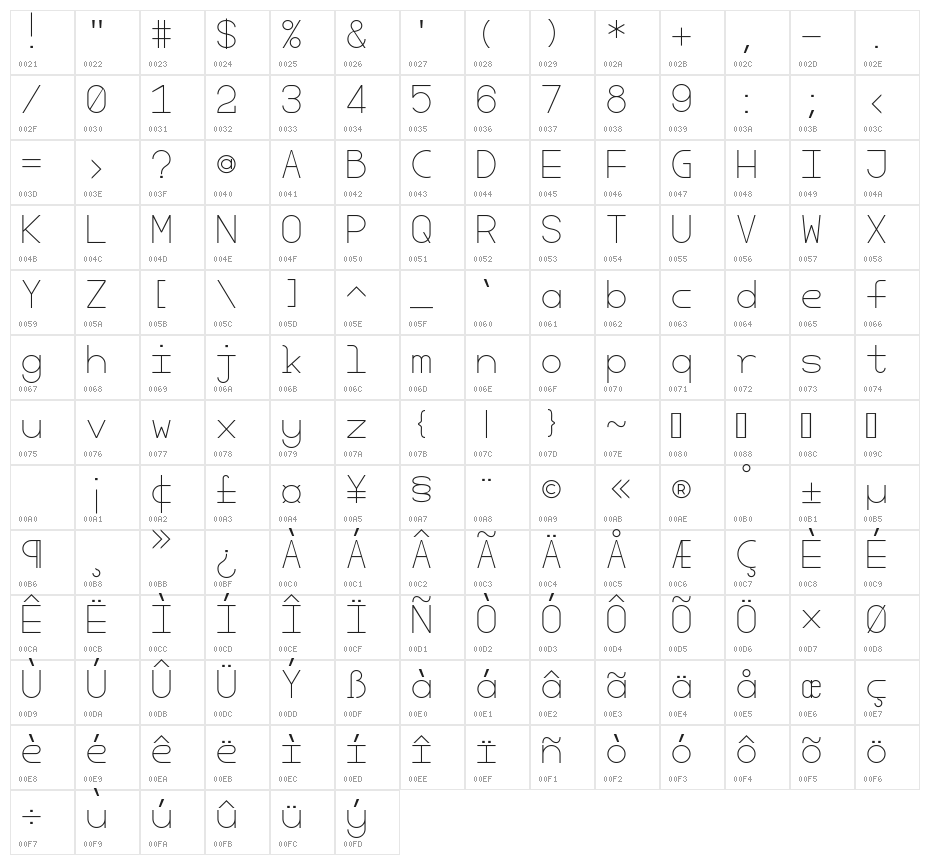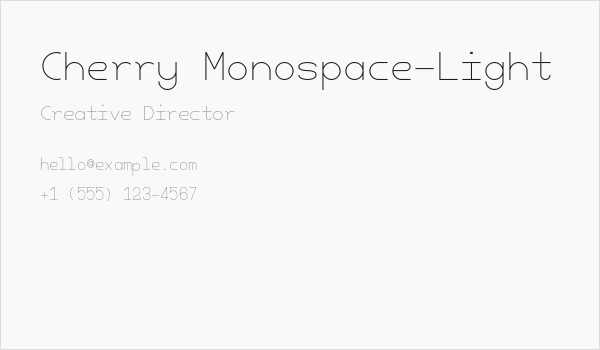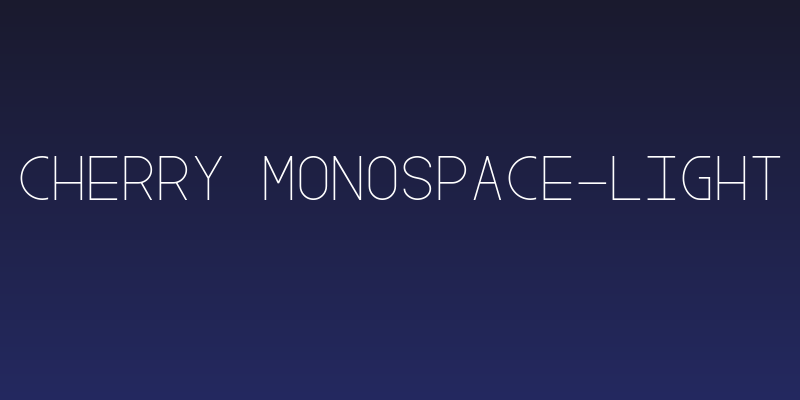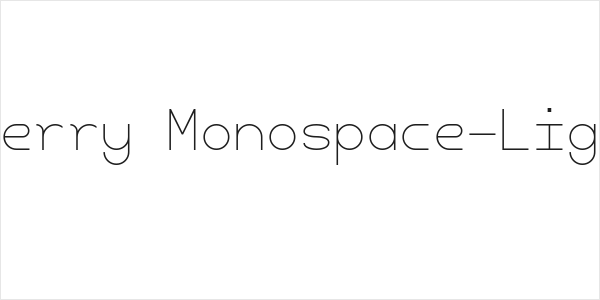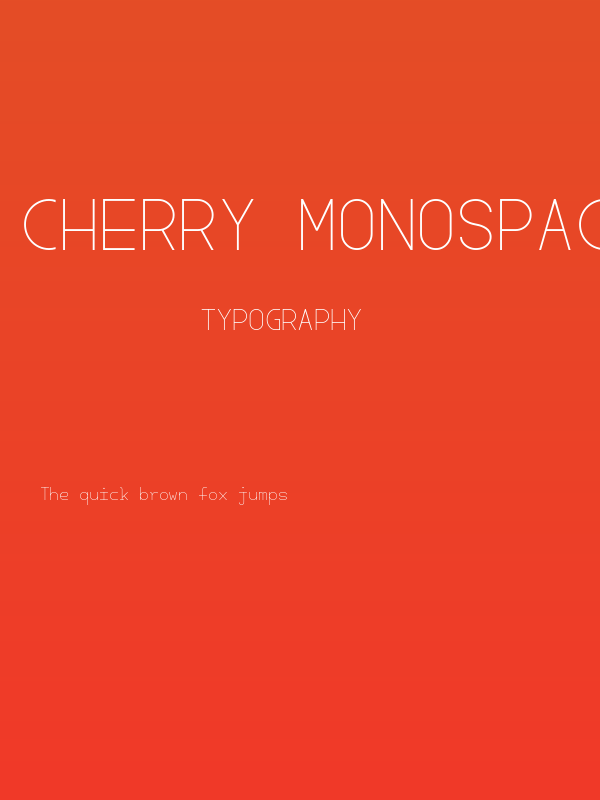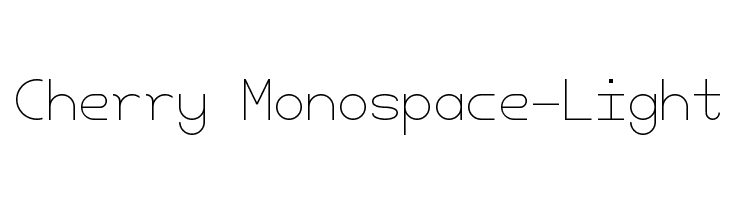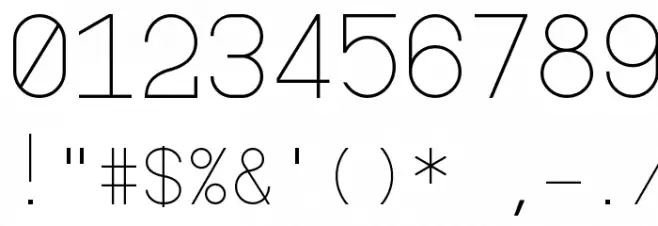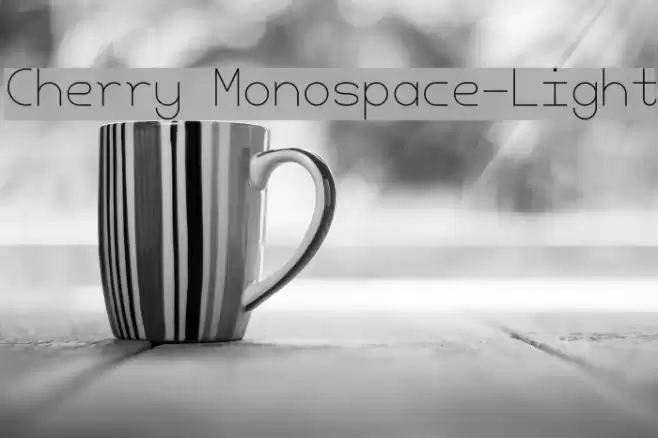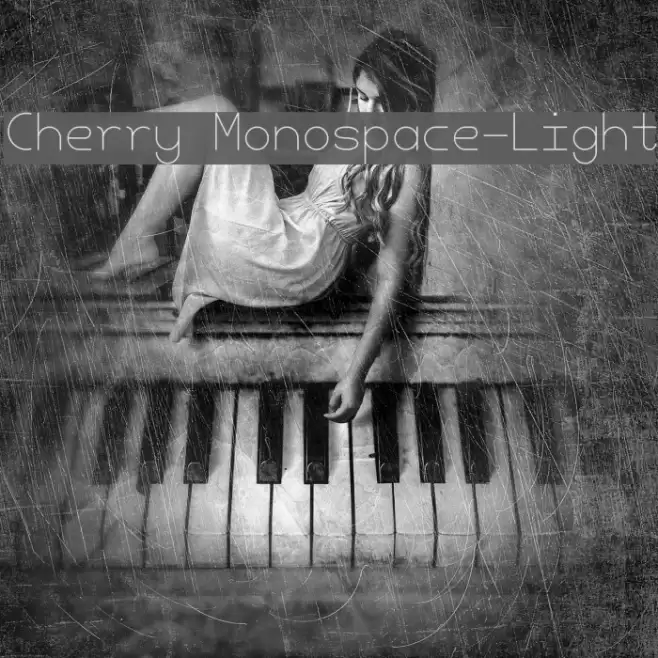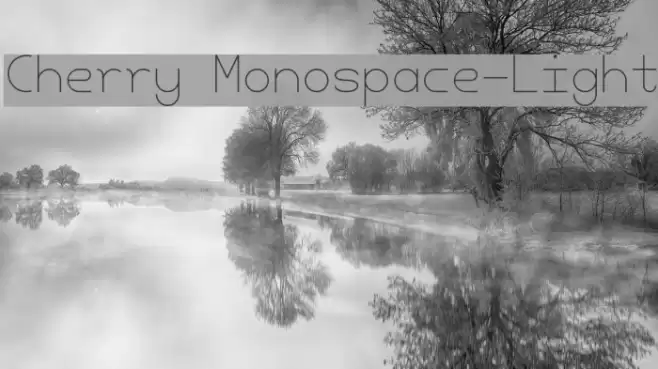
Cherry Monospace-Light Font
| Caz de utilizare | Coding, Technical documentation, Minimalist design |
| Proiecte propuse | Ideal for coding, technical documentation, minimalist design projects, and modern branding. |